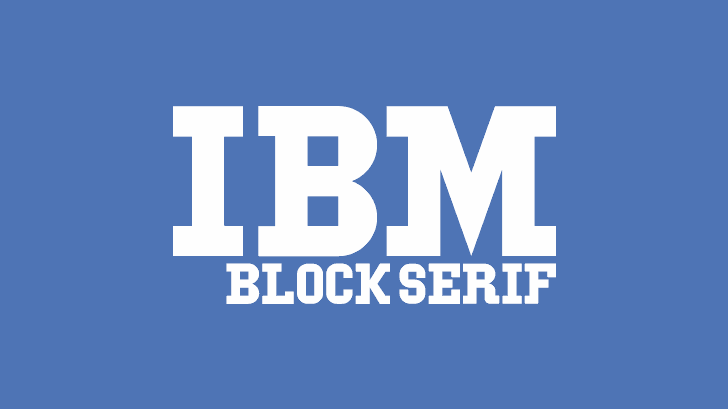
A IBM Block Serif é uma slab serif font criada por Thomas Kong em 2015. Esta elegante escolha de letras combina elementos modernos com a simplicidade clássica do tipo serif, resultando num visual amigável e profissional. O nome “IBM Block Serif” é uma referência direta à IBM Corporation e às suas soluções tecnológicas robustas e duradouras. Seja para uso em websites, impressões ou gráficos digitais, esta fonte oferece um contraponto sólido e estiloso para qualquer design. Ideal tanto para textos informativos quanto para gráficos de marca e logotipos, a IBM Block Serif é uma excelente opção para quem busca uma solução robusta e visualmente atrativa. Como designer Hamilton, Thomas Kong soube capturar a essência da IBM em cada traço da fonte, criando um elemento visual que representa não apenas tecnologia, mas também confiabilidade e modernidade.